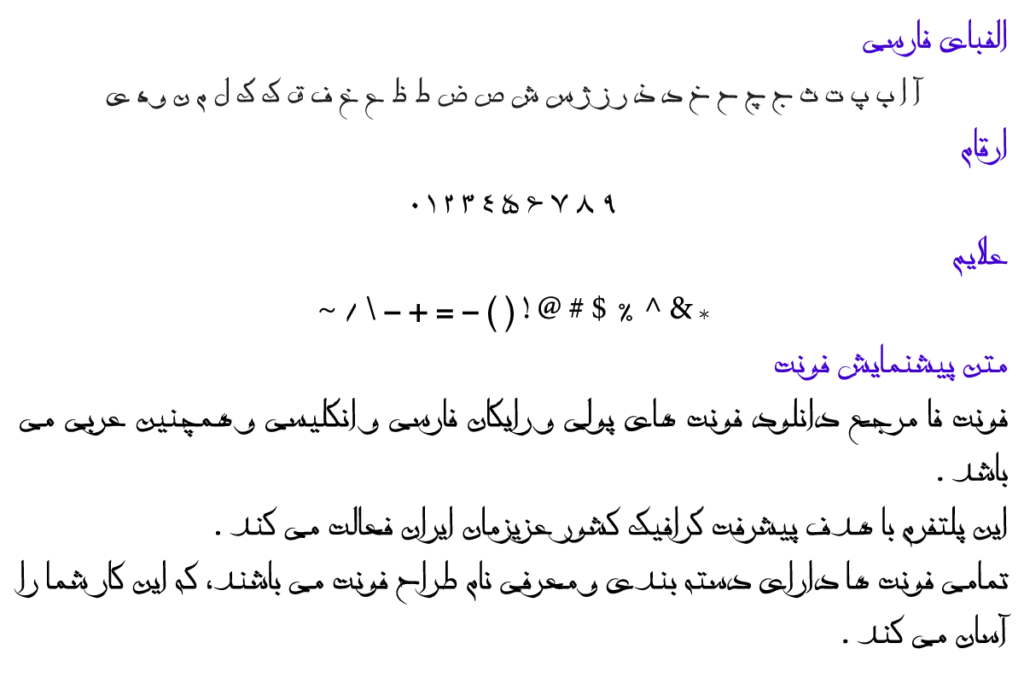
فونت فارسی گل – Gol
طراح فونت: توحید گلکارزاده نوع فونت: فونت فانتزی
توضیحات و معرفی فونت گل
فونت فارسی گل ( Gol ) از مجموعه فونت های آزاد می باشد، و نیز نوع فونت فانتزی می باشد.
فونت خوشگل مربوط توسط توحید گلکارزاده طراحی و ساخته شده است.
این تایپ فیس تفاوت زیادی به فونت گلدون داره با این تفاوت که روی نوشته ها اثری از گل نیست.
در این تصویر میتوانید پیشنمایش این فونت زیبای فانتزی را با شعر وطنم ببینید.